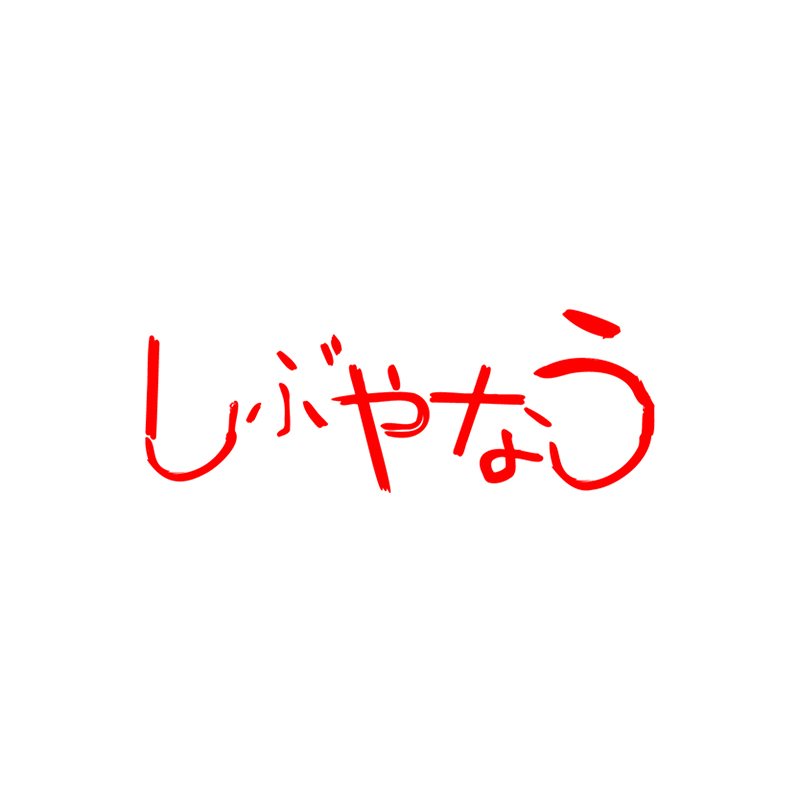
しぶやなう
どこなう?
Artist劉 樹岳
Designer三股条太郎
Organizationワークセンターひかわ
スティックと手書きの組み合わせは大変だったけどがんばれた。スティックを短いのと長いのをどう使うかを考えた。筆ペンで自分でも書けたのは楽しかった。(劉 樹岳)
「泥臭くいこうよ 整えすぎないでね」というテーマにそって楽しくみんなで制作できました!(三股条太郎)
制作したフォントを使ったひねりの効いたキャッチコピー。 年齢性別問わずグローバルに活用されたいパターンです。(ワークセンターひかわ)